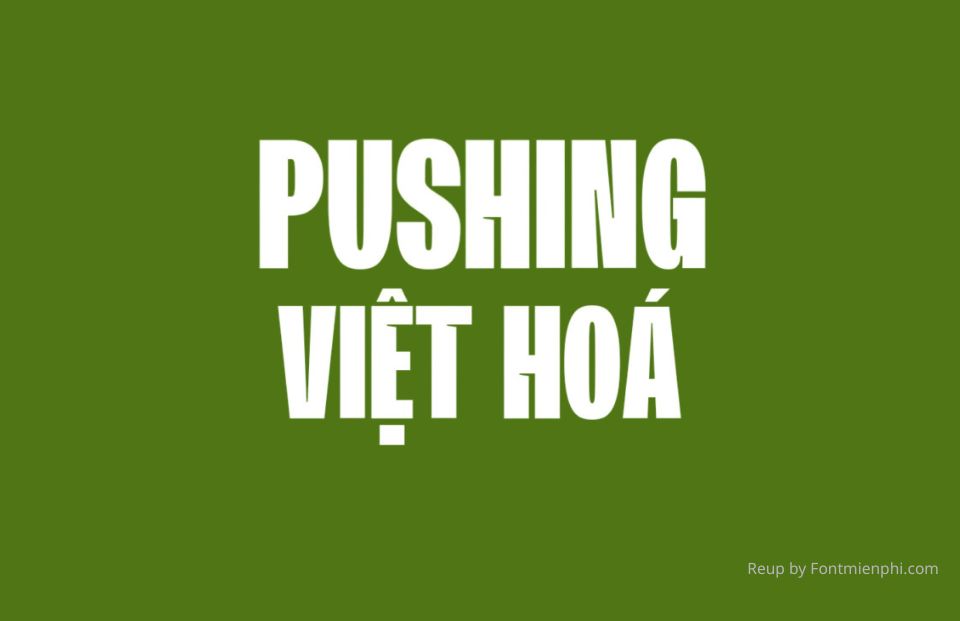
Font Việt hóa 1FTV VIP Pushing là một trong những bộ phông chữ Display nghệ thuật ấn tượng, được tinh chỉnh hoàn hảo dành riêng cho các nhà thiết kế đồ họa và sáng tạo nội dung tại Việt Nam. Sở hữu đường nét mạnh mẽ, phá cách cùng hơi thở hiện đại, bộ font này mang đến giải pháp thị giác vượt trội cho mọi dự án truyền thông và xây dựng thương hiệu. Bản Việt hóa chuẩn xác đảm bảo tính thẩm mỹ cao nhất, giúp ngôn ngữ tiếng Việt được thể hiện trọn vẹn mà không gặp bất kỳ rào cản kỹ thuật nào.
Font Việt Hóa 1FTV VIP Pushing – Đột Phá Thị Giác Đẳng Cấp Cho Dự Án Thiết Kế Hiện Đại
Trong thời đại mà trải nghiệm thị giác đóng vai trò quyết định đến sự chú ý của khách hàng, việc lựa chọn một bộ typography độc đáo là chìa khóa then chốt tạo nên sự khác biệt. Font Việt hóa 1FTV VIP Pushing ra đời như một câu trả lời hoàn hảo cho nhu cầu tìm kiếm sự mới lạ, cá tính và tràn đầy năng lượng. Bộ phông chữ này kết hợp hài hòa giữa cấu trúc hình học chuẩn mực và nét chấm phá nghệ thuật đương đại, tạo nên cảm giác chuyển động không ngừng đúng như tên gọi “Pushing”.
Được phát triển và tối ưu bởi đội ngũ kỹ thuật giàu kinh nghiệm, phiên bản VIP này không chỉ kế thừa toàn bộ tinh hoa từ bản gốc mà còn được vẽ lại dấu tiếng Việt vô cùng tỉ mỉ. Các dấu thanh như sắc, huyền, hỏi, ngã, nặng và các ký tự đặc trưng như â, ê, ô, ơ, ư, đ được cân đối kích thước, khoảng cách và độ nghiêng chính xác tuyệt đối, tránh hiện tượng vỡ bố cục hoặc chồng chéo ký tự thường gặp ở các font chưa được chuẩn hóa.
1. Bộ ký tự Tiếng Việt chuẩn hóa toàn diện, dấu thanh hài hòa
Chức năng cốt lõi và quan trọng nhất của phiên bản 1FTV VIP Pushing chính là hệ thống ký tự tiếng Việt được Việt hóa theo chuẩn Unicode quốc tế. Từng dấu phụ được tinh chỉnh thủ công để đảm bảo giữ nguyên tinh thần thiết kế góc cạnh, cá tính của bản gốc. Khoảng cách giữa các ký tự (kerning) và độ cao dòng (leading) được căn chỉnh tối ưu, giúp câu chữ liền mạch, thanh thoát, không gây rối mắt khi hiển thị trên cả đoạn văn ngắn hay những dòng tiêu đề lớn.
2. Phong cách Display mạnh mẽ, mang đậm dấu ấn thị giác độc bản
1FTV VIP Pushing được định hình với ngôn ngữ thiết kế chắc khỏe, nét chữ dày dặn kết hợp cùng những góc vát dứt khoát. Điểm đặc biệt này tạo ra một ấn tượng thị giác vô cùng sâu sắc ngay từ cái nhìn đầu tiên, rất phù hợp cho:
• Thiết kế Key Visual, Poster, Banner quảng cáo sự kiện âm nhạc, thể thao, eSports.
• Bộ nhận diện thương hiệu cho các ngành hàng thời trang đường phố (streetwear), công nghệ, phòng gym hoặc đồ uống năng lượng.
• Thiết kế bìa sách, tạp chí nghệ thuật, album cover mang xu hướng vị lai (futuristic) hoặc phong cách cyberpunk, brutalism.
• Tiêu đề thumbnail YouTube, video intro trên TikTok giúp tăng tỷ lệ nhấp chuột (CTR) ấn tượng.
3. Hỗ trợ tính năng OpenType thông minh và hệ thống ký tự thay thế (Glyphs) phong phú
Bộ font được tích hợp đầy đủ các tính năng OpenType cao cấp, cho phép người dùng tùy biến linh hoạt trong quá trình dàn trang và thiết kế đồ họa. 1FTV VIP Pushing cung cấp nhiều ký tự thay thế (stylistic alternates) và chữ ghép (ligatures) nghệ thuật, giúp các designer dễ dàng sáng tạo nên những biểu trưng logo, typography chữ lồng độc đáo mà không tốn quá nhiều thời gian can thiệp vector thủ công.
4. Khả năng tương thích linh hoạt trên đa nền tảng và phần mềm
• Phần mềm đồ họa chuyên nghiệp: Adobe Photoshop, Illustrator, InDesign, CorelDRAW.
• Công cụ dựng phim và kỹ xảo: Adobe Premiere Pro, After Effects, DaVinci Resolve, CapCut PC.
• Nền tảng thiết kế UI/UX và trực tuyến: Figma, Canva, Sketch, Adobe XD.
• Tối ưu hóa hiển thị trên giao diện Website và ứng dụng di động mà không gây giật lag hay giảm tốc độ tải trang.
5. Tối ưu hóa hiển thị đa độ phân giải và chất lượng in ấn chuyên nghiệp
Được xây dựng trên nền tảng vector siêu mịn, bộ font đảm bảo chất lượng hiển thị sắc nét từ màn hình kỹ thuật số độ phân giải cao (Retina, 4K) cho đến các sản phẩm in ấn khổ lớn ngoài trời như billboard, backdrop sự kiện. Các nét cắt và tiếp điểm của chữ không bị răng cưa khi phóng to kích thước cực đại, giúp ấn phẩm hoàn thiện luôn đạt độ tinh xảo cao nhất.
Bí quyết ứng dụng hiệu quả Font Việt hóa 1FTV VIP Pushing trong thiết kế
Để phát huy tối đa sức mạnh của 1FTV VIP Pushing, bạn nên lưu ý một số nguyên tắc kết hợp typography sau:
1. Sử dụng làm điểm nhấn chính: Hãy ưu tiên dùng font này cho các cụm tiêu đề (Headline), khẩu hiệu (Slogan), từ khóa chính hoặc con số ấn tượng.
2. Phối hợp font chữ phụ trợ tương phản: Nên kết hợp 1FTV VIP Pushing với các bộ font Sans-serif trung tính, tối giản và dễ đọc (như Montserrat, Roboto, Inter, Be Vietnam Pro) cho phần nội dung chi tiết (Body text) để tạo sự cân bằng thị giác.